Di dunia jualan font, desain keren saja nggak cukup.
Kami pernah ada di posisi itu—bikin font berhari-hari, penuh semangat, lalu diunggah ke marketplace dengan harapan tinggi… hanya untuk melihat angka unduhan yang stagnan.
Dan itulah titik baliknya. Kami sadar, ada “rahasia” yang tidak banyak dibagikan: cara menyampaikan font-mu ke dunia.
Artikel ini adalah catatan pengalaman kami—tim Figuree Studio. Tanpa teori rumit, tanpa jargon. Cuma cerita dan strategi yang terbukti berhasil.
Font pertama yang kami unggah penuh optimisme… berakhir sunyi.
Bukan karena jelek. Desainnya rapi, bentuk hurufnya menarik. Tapi kami lupa satu hal penting: cerita di balik font itu sendiri.
Lalu lahirlah Back Wild.
Sebuah font graffiti. Tapi bukan yang garang atau berteriak. Justru sebaliknya—Back Wild tampil sederhana, dengan lekukan yang gemuk dan playful, hampir seperti gelembung di dinding kosong yang minta diisi warna.
Awalnya ia biasa saja. Tidak banyak yang melirik.
Namun ketika kami tulis ulang deskripsinya, semuanya berubah. Kami berhenti menjual bentuk, dan mulai menjual rasa. Kami bicara tentang energi positif, tentang nostalgia mural jalanan, tentang keberanian bermain di ruang kreatif yang fun.
Dan… boom.
Beberapa minggu kemudian, Back Wild masuk daftar font populer di Envato Elements. Berbulan-bulan ia bertahan di sana, tanpa iklan, tanpa strategi marketing rumit.
Hanya karena satu hal: narasi yang kena di hati.
Bayangkan ini: kamu lagi scroll 100 font di halaman marketplace. Apa yang bikin kamu berhenti?
Yup—preview image.
Itu kenapa kami mulai memperlakukan cover preview seperti poster film. Harus punya cerita, suasana, bahkan sedikit drama.
Gunakan grid layout, kontras warna yang tepat, dan real-world application (mockup packaging, branding, signage). Bikin klien membayangkan font kamu dipakai di proyek mereka.
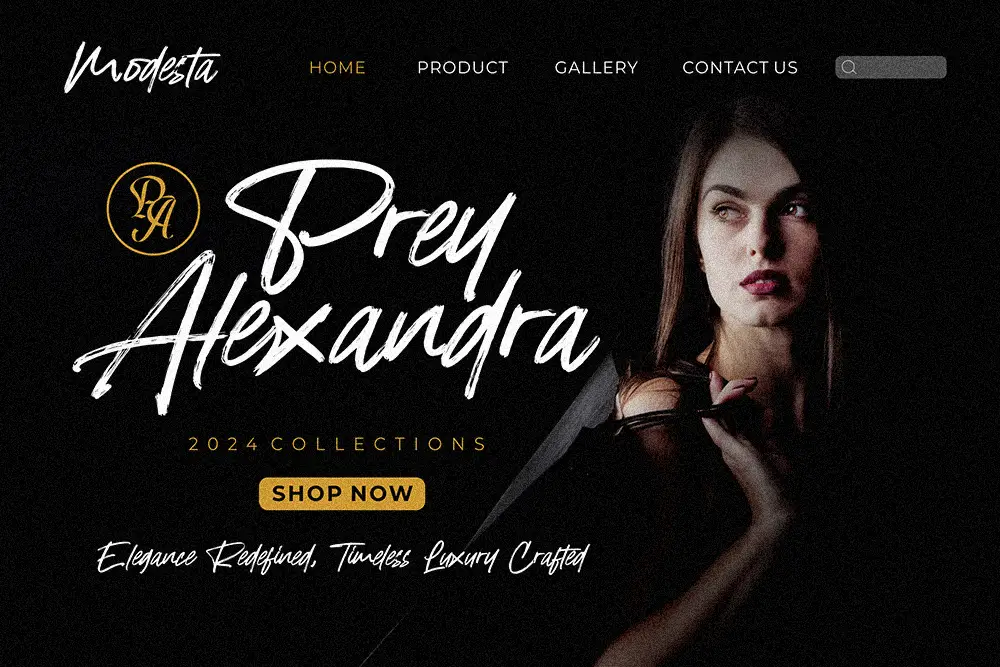
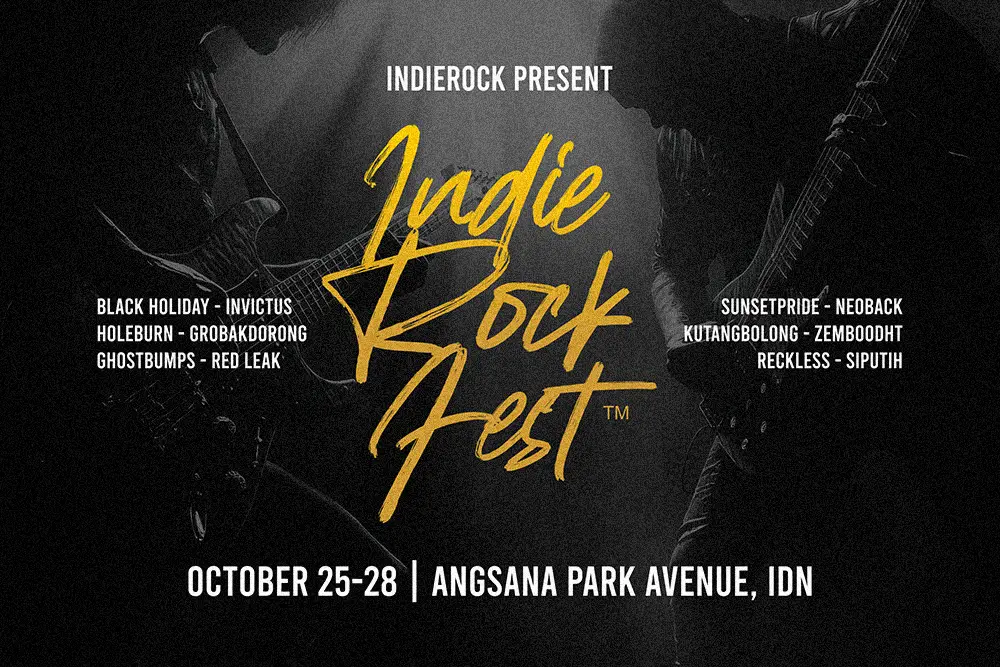
Preview font Roadpunks yang menampilkan fungsi font sebagai Headline dan Logo sebuah website, dan juga apabila font tersebut digunakan sebagai element desain utama sebuag poster konser musik.
Marketplace itu punya algoritma. Dan salah satu yang paling penting: fresh item boost.
Kalau kamu upload 10 font sekaligus, cuma satu yang mungkin dapat spotlight. Tapi kalau kamu upload satu per minggu, semua punya kesempatan naik.
Ini bukan sekadar strategi—ini ritme.
Kami suka diskon. Tapi bukan diskon asal-asalan.
Diskon harus ada ceritanya: launching, bundling, seasonal drop. Tapi jangan sampai menjual font bagus seharga kopi sachet cuma demi “kelihatan laris.”
Ingat, harga juga membentuk persepsi.
Desain kamu nggak akan ditemukan kalau kamu pakai deskripsi seperti “font keren untuk desain.” Marketplace butuh keyword yang spesifik.
Gunakan tools seperti:
Masukkan kata kunci dengan natural. Jangan spam. Tapi pastikan keyword itu muncul di judul, deskripsi awal, dan nama file jika memungkinkan.
Kami sadar, banyak buyer memutuskan beli karena percaya pada desainer di balik font itu.
Jadi jangan biarkan halaman profil kamu kosong. Tulis bio yang jujur dan menarik. Sertakan link ke website atau social media.
Sampaikan siapa kamu, apa yang kamu suka buat, dan kenapa kamu peduli pada desain.
Font kamu lucu. Yang berikutnya? Garang. Yang ketiga? Retro horror.
Sulit buat pembeli mengingat siapa kamu jika kamu terlalu random. Pilih 1–2 gaya utama dan bangun “semesta font” kamu di situ.
Contohnya? Kami bangun lini graffiti-style seperti Brick Edgie dan Urban Hope. Hasilnya, buyer yang suka gaya itu akan balik lagi.
Marketplace senang kalau kamu bawa traffic dari luar. Pinterest, Instagram, TikTok, bahkan blog pribadi bisa bantu.
Tim kami pernah dapat boost traffic hanya dari satu pin Pinterest yang viral.
Kadang pasar terbesar datang dari ceruk terkecil. Kami pernah merasakan sendiri saat merilis Grims Acid—sebuah font bertema horor yang justru tampil dengan gaya simpel dan clean.
Tidak ada darah, tidak ada efek terbakar. Justru Grims Acid tampil kontras dengan cover preview hitam dan hijau terang yang minimalis dan mencolok. Dan itulah yang menarik perhatian komunitas film indie dan desainer alternatif.
Eksplorasi gaya baru bisa memperluas pasar, selama tetap punya benang merah dengan arah visualmu.
Marketplace bukan hanya tempat jualan, tapi juga tempat interaksi. Pembeli yang nanya dan cepat dibalas cenderung lebih percaya dan langsung beli.
Kami bahkan pernah dapat deal corporate hanya karena respons cepat di kolom komentar.
Awal kami bikin font, kami pakai spidol Snowman seribuan yang ada di rumah. Sederhana, tapi dari situ lahir ide untuk mengeksplor goresan organik dan tekstur nyata. Sederhana, tapi dari situ lahir ide untuk mengeksplor goresan organik dan tekstur nyata.